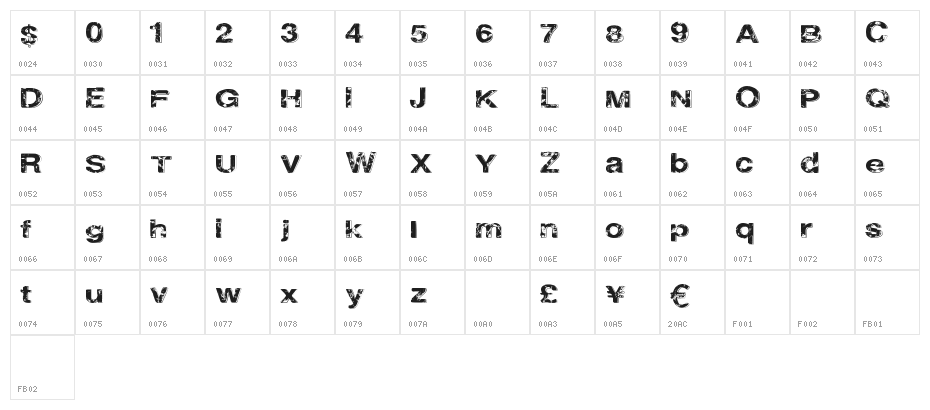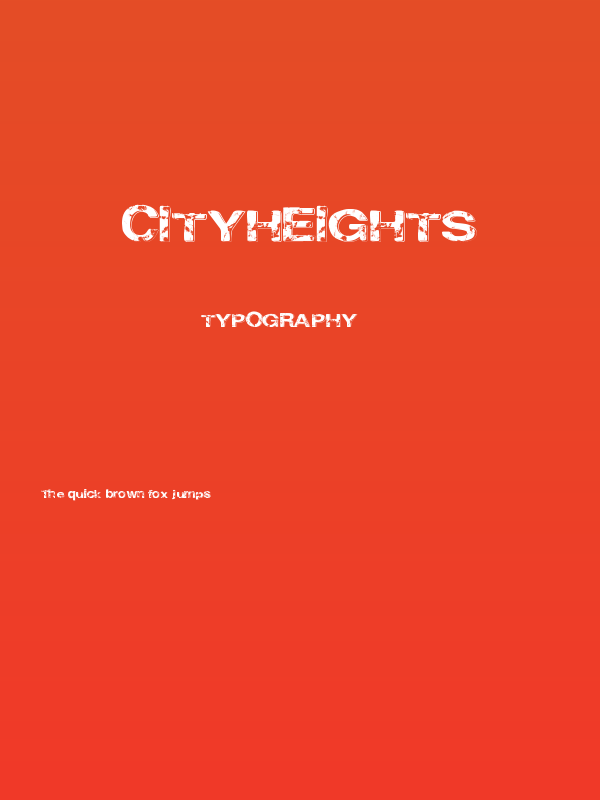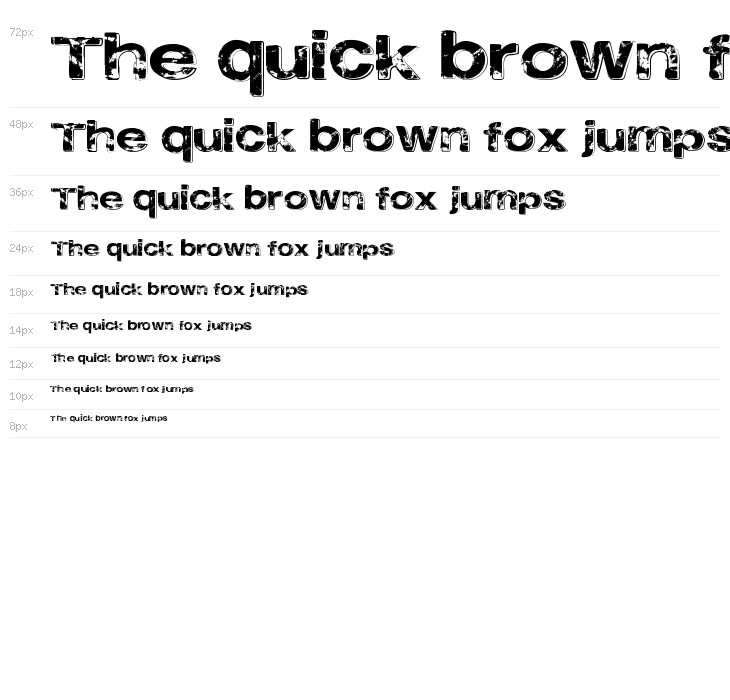
CityHeights Font
✎ Distorted Eroded
| Categorie | Distorted Eroded |
| Stile generale | Urban, Grunge, Vintage |
| Progetti proposti | Ideal for album covers, posters, streetwear branding, and urban-themed designs. |